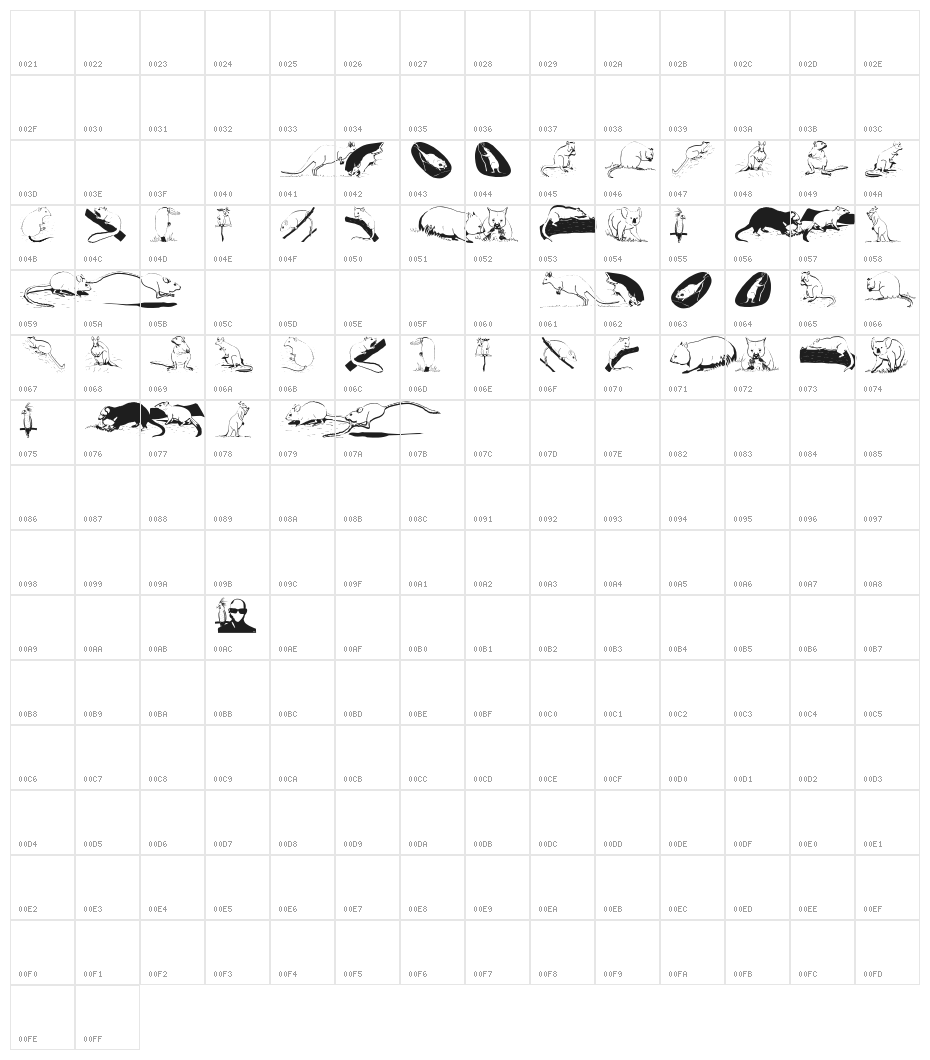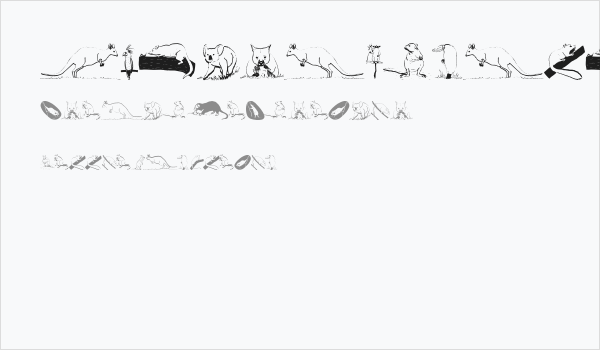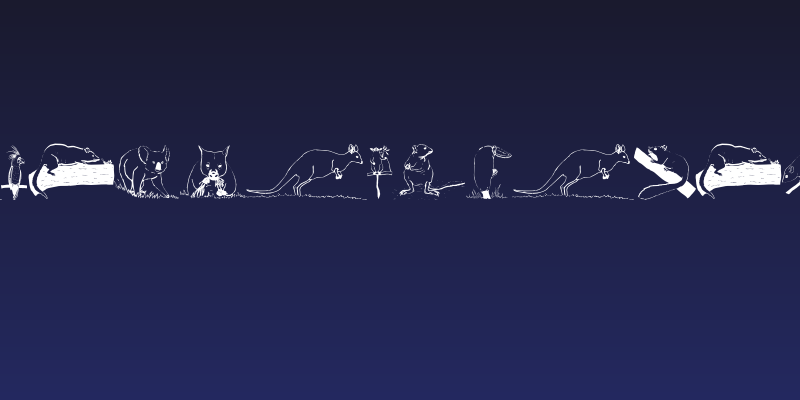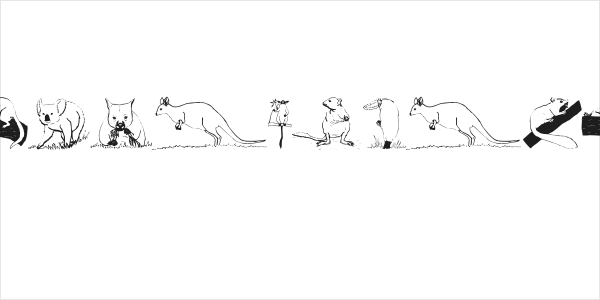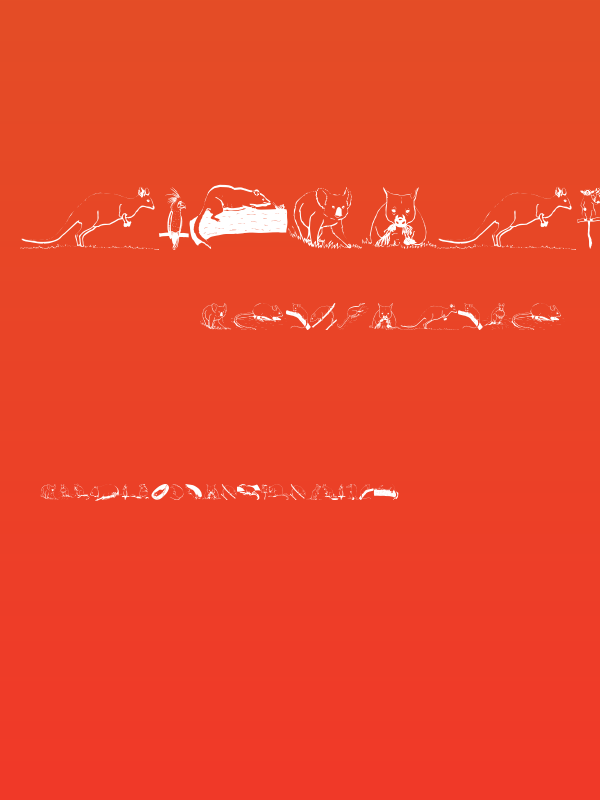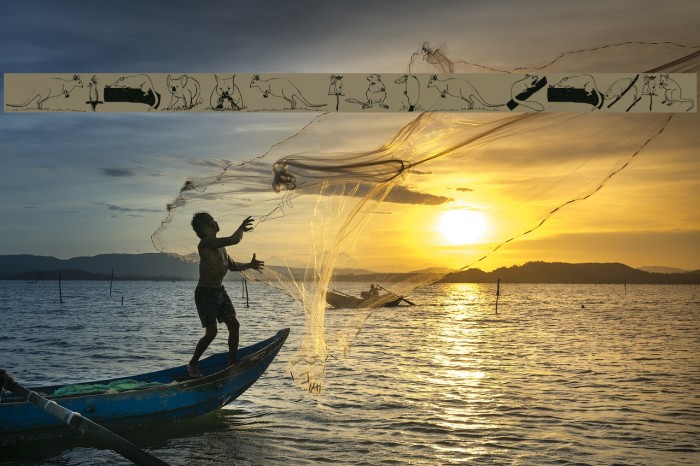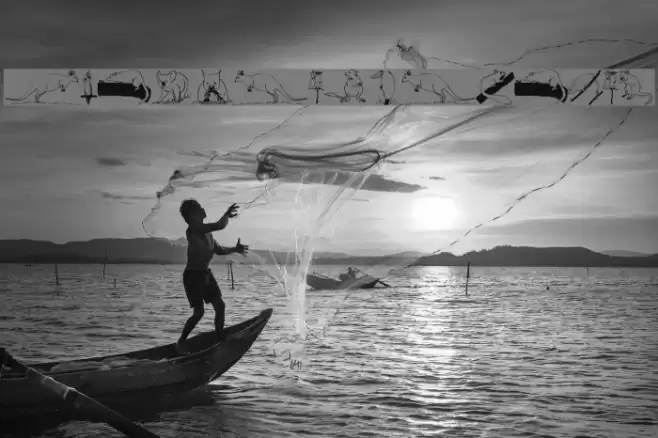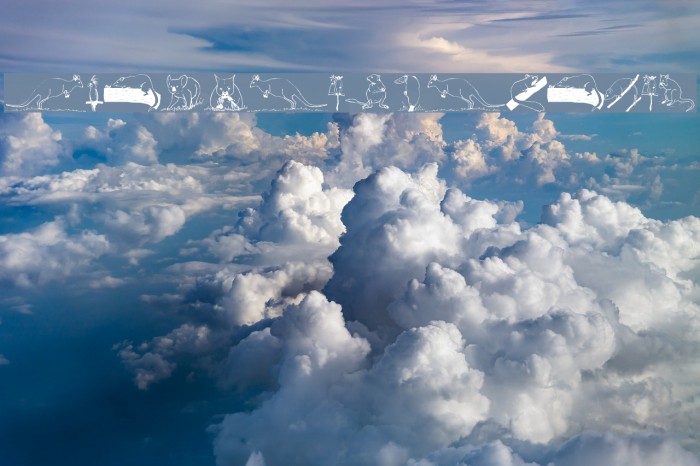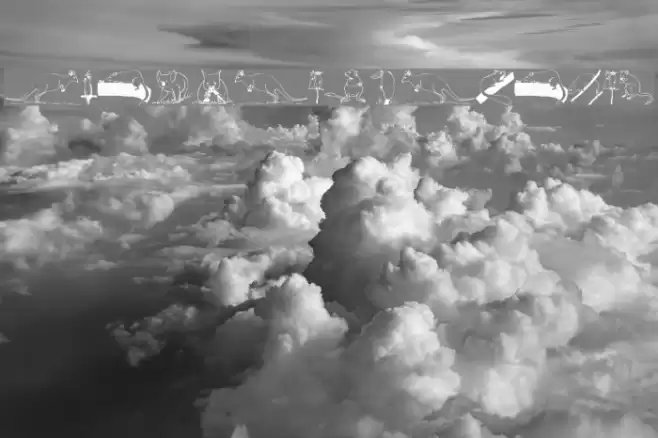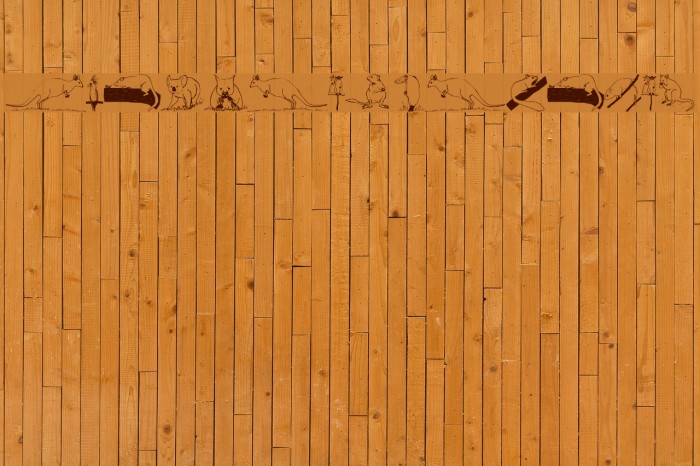
AustranimalsOne Font
| Caso de uso | Logos, Posters, Educational Materials |
| Projetos propostos | Ideal for children's books, educational materials, wildlife-themed posters, and playful branding. |